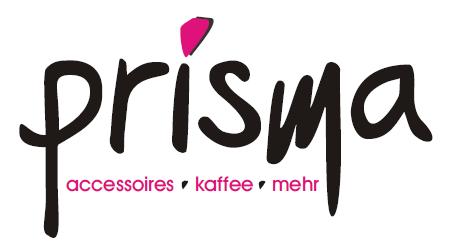
Welche Schrift (vermutlich mit Corel Draw erstellt) ist das?
Die beigefügte Datei zeigt das Logo meines - vor einiger Zeit übernommenen - Geschäftes. Da ich die Schrift für Flyer etc. weiter verwenden möchte, wüsste ich gerne, um welche Schriftart es sich dabei handelt. Bin für jeden Tip dankbar :)
Ich gehe da mit deiner Vermutung konform, dann ist es aber keine Schrift, schon gar nicht mit Namen, sondern eben frei gestaltete und selbst gezeichnbete Vektor-Objekte in Form von Buchstaben. Ein weg, der sich bei Logos mit nur wenigen Buchsteben eigentlich immer anbietet, kann man so eben ein Logo erstellen, dass sich eben nicht mal schnell nachsetzen lässt,